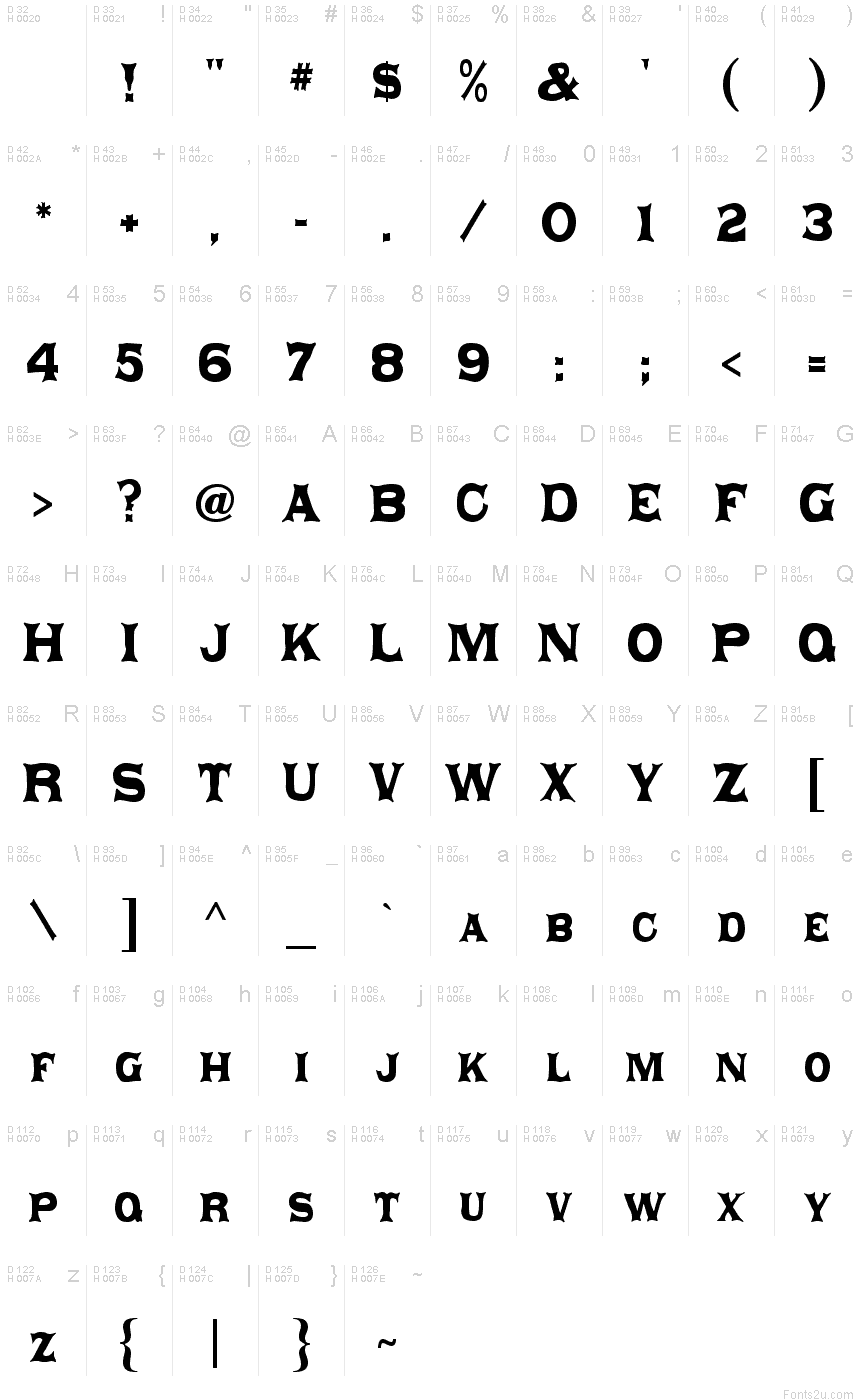
Daisy هو خط عرض (display font) مجاني بطابع "ويسترن" (Western) صممه Richard William Mueller عام 1992. يستحضر الخط الأجواء القاسية للحدود الأمريكية من خلال منحنيات عريضة، ووصلات متصلة بدقة، وحواف حادة تجعل الحروف الكبيرة تبدو منحوتة وليست مرسومة فقط. تتمتع الحروف بجرأة ملصقات الأفلام القديمة، لكن التشويه الطفيف يضفي عليها طابعاً غريباً ومميزاً بعيداً عن الطراز الريفي التقليدي.
يعتبر الخط مثالياً لهوية "الصالونات" (Saloon)، ومنشورات مسابقات الروديو، وأغلفة الروايات الغربية، والعناوين، ولافتات البارات أو الأماكن التي تحتاج إلى خط مجاني يتمتع بهذا القدر من النكهة التاريخية. استخدمه للعناوين الكبيرة أو الاقتباسات أو الحروف الاستهلالية عندما تبحث عن تلك اللمسة الدرامية المتربة دون المبالغة في الغرابة.